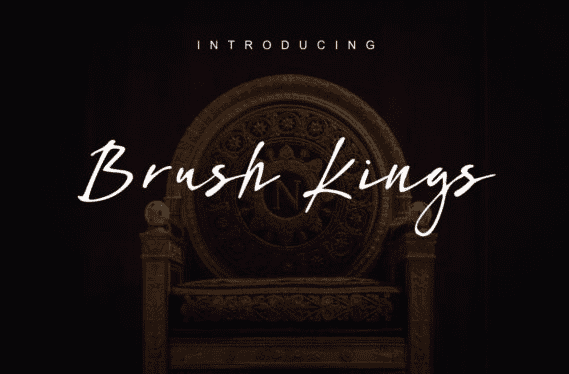
Название: Brush Kings Font
Brush Kings - это естественный шрифт скрипта.
Он идеально подходит для логотипов, цитат, плакатов, игривых надписей, одежды и любого другого дизайна, который нуждается в уникальном прикосновении.